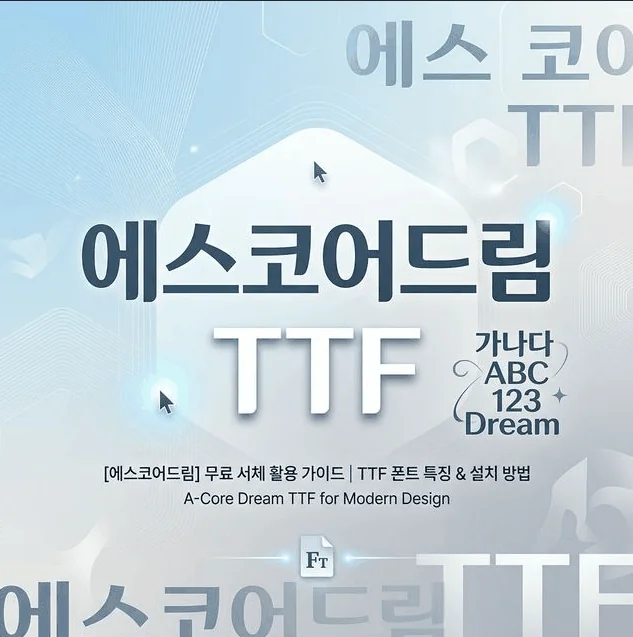
웹 디자이너로 활동하며 수많은 서체를 다뤄봤지만, "가장 신뢰할 수 있는 산세리프(Sans-serif)"를 하나만 고르라면 주저 없이 에스코어드림(S-Core Dream)을 추천합니다. 정교하게 설계된 꽉 찬 직사각형의 미학, 그리고 얇은 굵기부터 두꺼운 굵기까지 이어지는 완벽한 밸런스는 실무에서 그 진가를 발휘합니다.
사실 블로그나 PPT, 그리고 기업의 웹사이트를 만들 때 가장 고민되는 것이 바로 '폰트'입니다. 너무 튀지 않으면서도 세련되어야 하고, 본문에서는 잘 읽혀야 하며 제목에서는 확실한 임팩트를 줘야 하죠. 이 까다로운 조건을 모두 만족시키며 심지어 상업적으로 써도 완전 무료인 서체가 바로 에스코어드림입니다.
1. 에스코어드림(S-Core Dream) 탄생 배경 및 정체성 🖋️
에스코어드림은 삼성그룹의 계열사인 에스코어(S-Core) 주식회사가 제작하여 2018년에 본격적으로 배포를 시작한 서체입니다. 에스코어는 '꿈(Dream)을 현실로 만든다'는 기업 철학을 바탕으로, 창작자들의 꿈을 돕기 위해 이 서체를 기획했다고 해요. 기업의 나눔 문화를 실천하는 아주 멋진 사례라고 볼 수 있습니다.
디자인적으로 가장 큰 특징은 '꽉 찬 직사각형 구조'입니다. 고딕 계열의 산세리프 서체이지만 자폭(글자의 가로 너비)이 일정하게 유지되어 텍스트가 정갈하게 정체되어 있는 듯한 느낌을 줍니다. 이는 사용자에게 '안정감'과 '전문성', 그리고 '신뢰'라는 심리적 메시지를 전달하게 됩니다. 대기업의 리포트나 관공서의 안내문, 그리고 세련된 스타트업의 랜딩 페이지에서 이 서체를 자주 볼 수 있는 이유도 바로 여기에 있습니다.
2. 9가지 굵기(Weight) 상세 가이드 및 활용 팁 💡
에스코어드림이 디자이너들에게 찬사를 받는 가장 큰 이유 중 하나는 바로 '9단계의 세밀한 가중치(Weight)'를 제공한다는 점입니다. 보통 무료 서체들은 2~3가지 굵기만 제공하는 경우가 많지만, 에스코어드림은 1부터 9까지 아주 촘촘한 시스템을 갖추고 있습니다.
1. Thin매우 얇은 외곽선, 감성적
2. ExtraLight세련된 보조 텍스트
3. Light본문의 품격을 높이는 굵기
4. Regular가장 대중적인 본문용
5. Medium강조하고 싶은 리드문
6. Bold소제목 및 핵심 강조용
7. ExtraBold유튜브 제목 0순위
8. Heavy강력한 임팩트, 광고 카피
9. Black압도적인 꽉 참, 메인 헤드라인
🌟 현업 디자이너의 활용 노하우 (Cheat Sheet)
• 유튜브 썸네일: 제목은 7 ExtraBold 또는 9 Black을 사용하고, 자간을 -5% 정도 주어 꽉 찬 느낌을 극대화하세요.
• 카드뉴스 본문: 가독성이 가장 좋은 단계는 4 Regular입니다. 소제목은 6 Bold를 사용해 위계를 나누세요.
• 스마트폰 시스템 폰트: 눈이 가장 편안한 굵기는 3 Light 또는 4 Regular입니다.
• 웹사이트 메인 카피: 배경 이미지가 화려하다면 1 Thin을 써서 세련된 느낌을 주거나, 반대로 아예 8 Heavy를 써서 텍스트 중심의 시각화를 시도해보세요.
귀여운 폰트도 좋지만, 가끔은 내 갤럭시 핸드폰을 깔끔한 직사각형 정석 폰트로 바꾸고 싶을 때가 있죠. 에스코어드림은 모바일 UI에서도 압도적인 가독성을 자랑합니다.
Q1. 유튜브 자막폰트로 어떤가요?
A1. 최고입니다. 특히 6 Bold 이상 굵기를 사용하면 가독성이 매우 뛰어납니다. 많은 대형 전문 유튜버들이 메인 서체로 사용하고 있습니다.
Q2. 인쇄물(포스터, 리플릿) 작업 시 주의점은?
A2. 글자가 꽉 찬 형태라 자간(Letter spacing)이 기본적으로 좁아 보일 수 있습니다. 본문용으로 쓸 때는 자간을 평소보다 2~3% 정도 늘려주면 여유로운 느낌을 줍니다.
Q4. 다른 삼성 폰트와 차이가 있나요?
A4. 삼성전자의 '삼성원(SamsungOne)' 서체와는 다릅니다. 삼성원은 사내용/제품용이지만 에스코어드림은 에스코어에서 대국민 공개를 위해 만든 오픈 라이선스 서체입니다.
Q5. 왜 500 같은 숫자가 썸네일에 나오나요?
A5. 간혹 폰트의 가중치를 숫자로 표기(400: Regular, 700: Bold 등)하는 경우가 있어 혼동이 올 수 있습니다. 에스코어드림은 1부터 9까지의 명칭을 사용하므로 이를 기준으로 기억하시면 좋습니다.
에스코어드림 폰트는 단순한 무료 선물을 넘어, 우리나라 창작 생태계를 풍요롭게 해주는 소중한 자산입니다. 한글의 아름다움을 현대적으로 가장 잘 해석한 서체 중 하나인 만큼, 이번 가이드를 통해 여러분의 작업물에 날개를 다셨길 바랍니다.